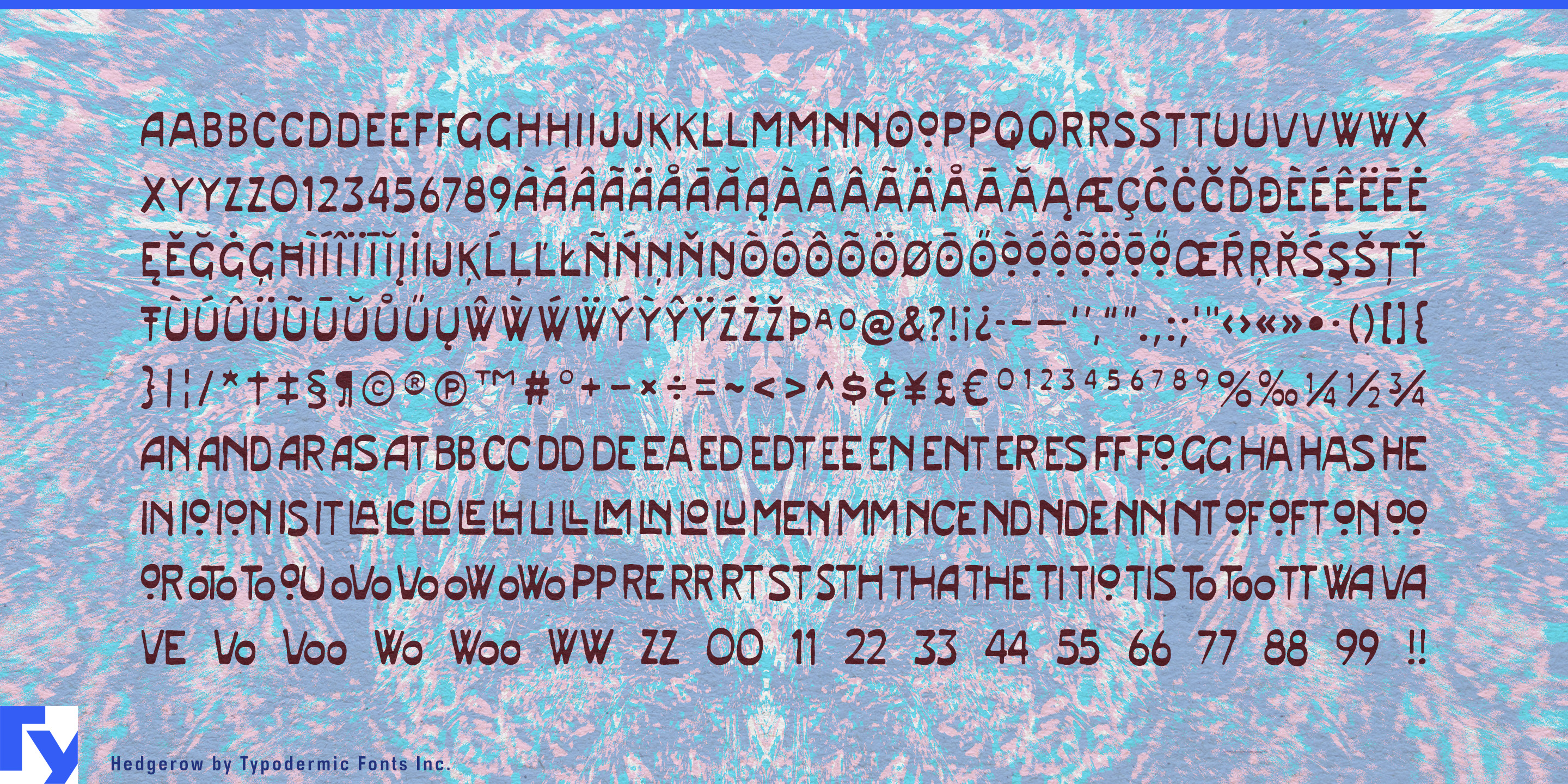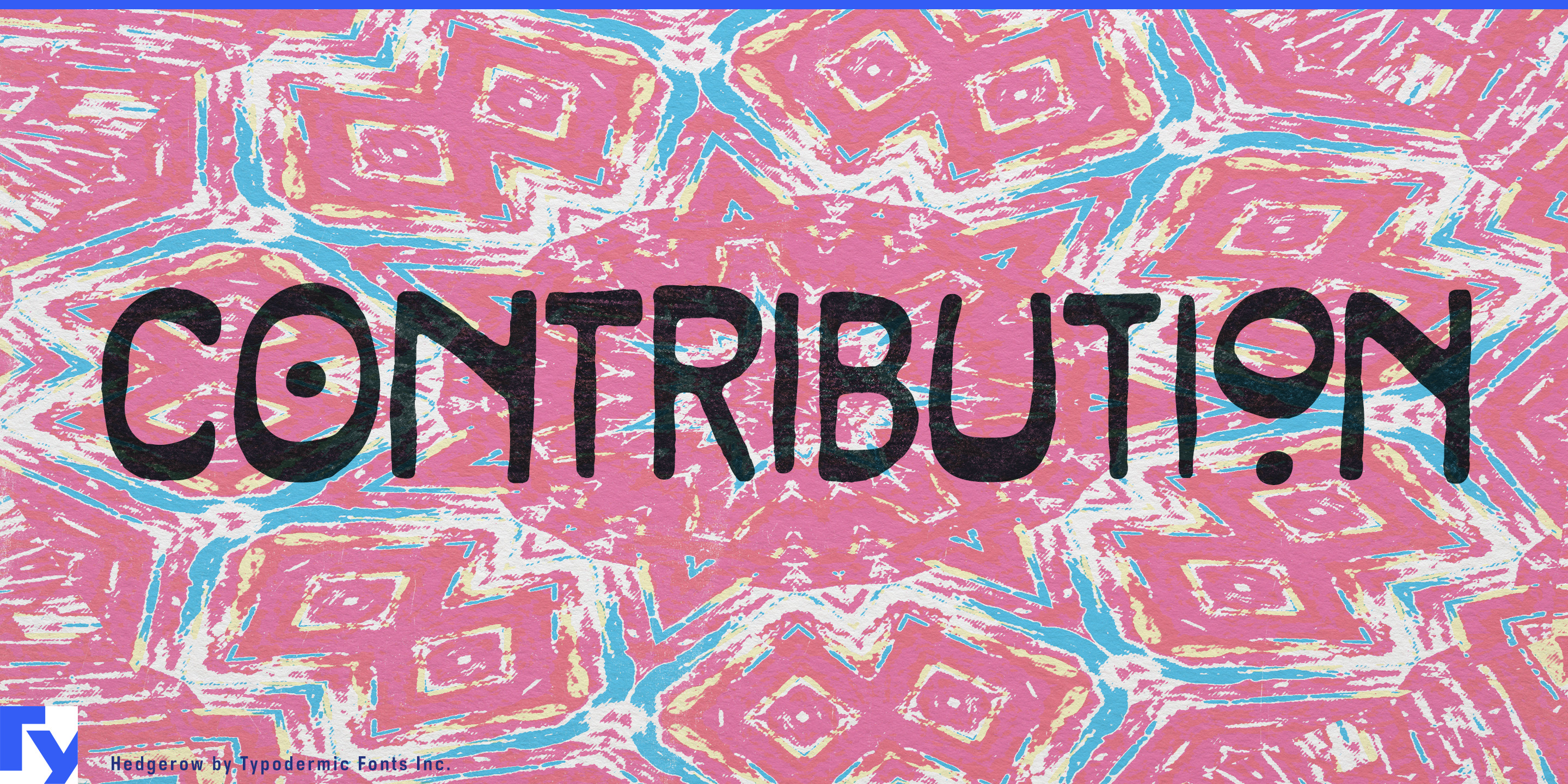
Hedgerow
Altmodische Verpackungsgestaltung lässt sich leicht übertreiben. Viktorianisches Ornament kann theatralisch werden, rustikale Schriftzüge können ins Volkstümliche kippen, und elegante Kalligrafie wirkt oft zu ausgefeilt. Hedgerow bietet einen anderen Weg: den kernigen Charakter kleingedruckter Kalligrafie, für den Display-Einsatz vergrößert.
Ausgangspunkt waren die eigentümlich ineinandergreifenden Schriftzüge in den Begleittexten von Led Zeppelin IV, erweitert durch Kalligrafie aus Arts & Crafts und Jugendstil. Hedgerow bewahrt die kompakte, aufrechte Qualität von Schriftzügen für kleine Druckgrößen. Vergrößert werden ihre schmalen Versalien, weichen Unregelmäßigkeiten und ineinandergreifenden Ligaturen zu einer markanten Display-Textur.
Das macht sie besonders nützlich für Produkte, die historischen Charakter ohne die übliche Formel gravierter Etiketten brauchen. Teedosen, Eingemachtes, pflanzliche Körperpflegeprodukte, Gartendüfte, Kräuterzubereitungen, Samenöle, traditionelle Süßwaren, Feinkost und ähnliche Waren können Hedgerow für Produktnamen, Sorten, Geschmacksrichtungen und kurze Werbezeilen nutzen. Mit leuchtenderen Farben und freundlichen Illustrationen kann sie nostalgisch-vertraut oder sogar niedlich aussehen. Dunklere Bilder können die fremdartigere Seite hervortreten lassen, die ihre Led-Zeppelin-Ursprünge andeuten.
Hedgerow passt auch ungewöhnlich gut zu historischer Fotografie und Archivgestaltung. Anmerkungen zu Daguerreotypien, Bildunterschriften auf Kabinettkarten, genealogische Publikationen, Museumsgrafiken, Dokumentarfilmtitel, historische Fotosammlungen und beiläufige Drucksachen in Historiendramen profitieren von Schriftzügen, die wie ein Etikett oder eine handschriftliche Notiz auf einem alten Druckerzeugnis wirken, statt wie eine große historische Schlagzeile.
Ihre Anmutung alter Samenkataloge macht Gartenbauthemen zu einem weiteren naheliegenden Einsatzfeld: Sortennamen, Samentütchen, Gärtnereimaterialien, Gartenprodukte, Gewächshausbedarf und botanische Überschriften passen alle zu ihren dichten kalligrafischen Formen. Hedgerow kann sich neben botanischen Stichen, verblassten Fotos oder zeitgenössischen Illustrationen einfügen und dabei einen beliebig rustikalen Eindruck vermeiden.
Hedgerow ist eine Versal-Display-Schrift, die sich besonders für konzentrierte Aufgaben wie Verpackungsvorderseiten, Titel, Überschriften, Etiketten, Anmerkungen und kurze Texte eignet. In größeren Schriftgraden zeigen die Ligaturen und kompakten kalligrafischen Formen jene Textur, die der Schrift ihre eigentümliche Mischung aus altmodischem Charme und leichter Fremdartigkeit gibt.